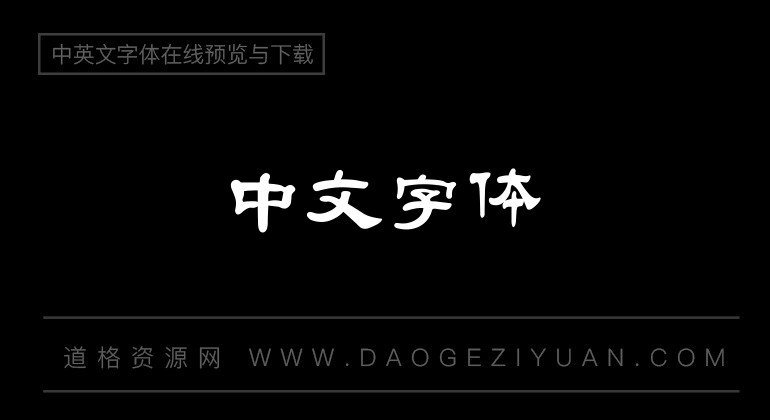
中国龙豪隶书
? 中国龙豪隶书是一种传统的书法字体,它是由宋代书法家李龙豪在宋朝时期发明的。它的特点是字体粗犷,笔画流畅,结构紧凑,笔划精细,笔法灵动,表达力强,构图巧妙,有时也有一些抽象的图形符号,给人以豪迈、雄浑的感觉。
中国龙豪隶书是一款非常不错的手写艺术字体,具有很好的视觉感,适合于文化类的宣传设计、商业类品牌的广告和产品包装设计以及个性化文字排版等较多场景。